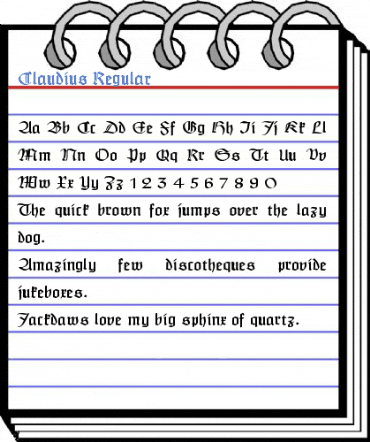
Claudius Regular Font
Copyright: Nach geschriebenen Vorlagen von Rudolf Koch stellte sein Sohn Paul Koch 1931-1934, also noch zu Lebzeiten seines Vaters, einen Grad der Schrift her; die uebrigen Grade wurden bis 1937 durch die Schriftgiesserei Gebr. Klingspor (Offenbach/M.) ergaenzt.
Designer: Rudolf Koch. Digitalisiert durch Dieter Steffmann, Kreuztal